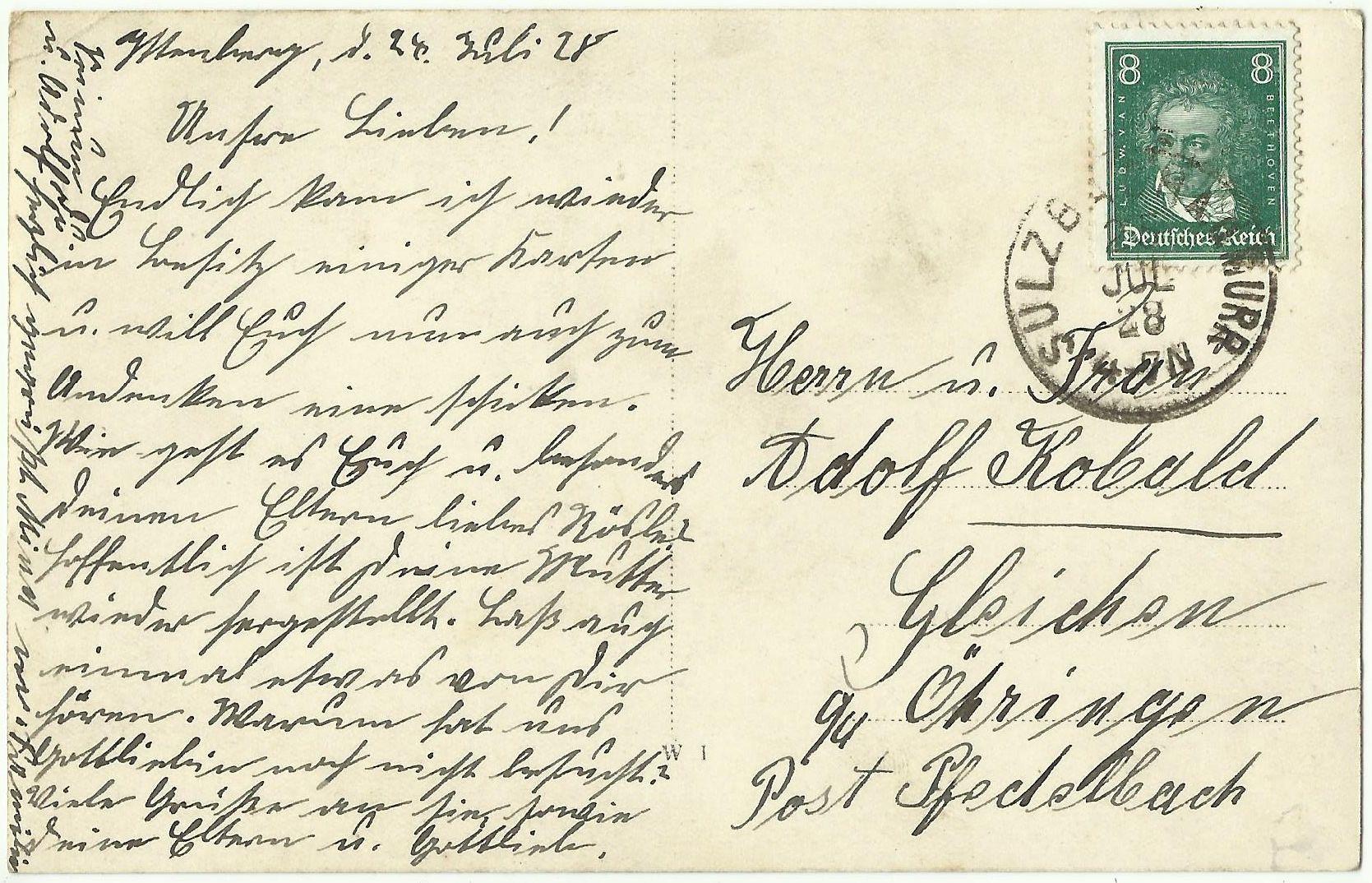
Herzlichen Danke für die schnelle Lösung. Sammle und verkaufe auch mal Postkarten. Da ist eben der Ort auch wichtig, da eine Fotopostkarte doch speziell ist. Doppel tt ist jetzt doch dann erkennbar.
Ittenberg passt auch zum Poststempel.
So bin ich drauf gekommen. Bei Wikipedia nach der Stadt des Poststempels gesucht, danach erst die Umgebung (erfolglos) abgesucht und dann die Ortsteile (erfolgreich).
Habe eine Postkarte, kann den Ort oben links nicht genau lesen. Wer kann helfen ?
Beim ersten Buchstaben  bin ich mir nicht sicher; kann ein I sein. Der zweite ist mit Sicherheit das lang-s, der dritte ein t, -- enberg .  Ohne zu wissen, ob es den Ort überhaupt gibt, oder gab.